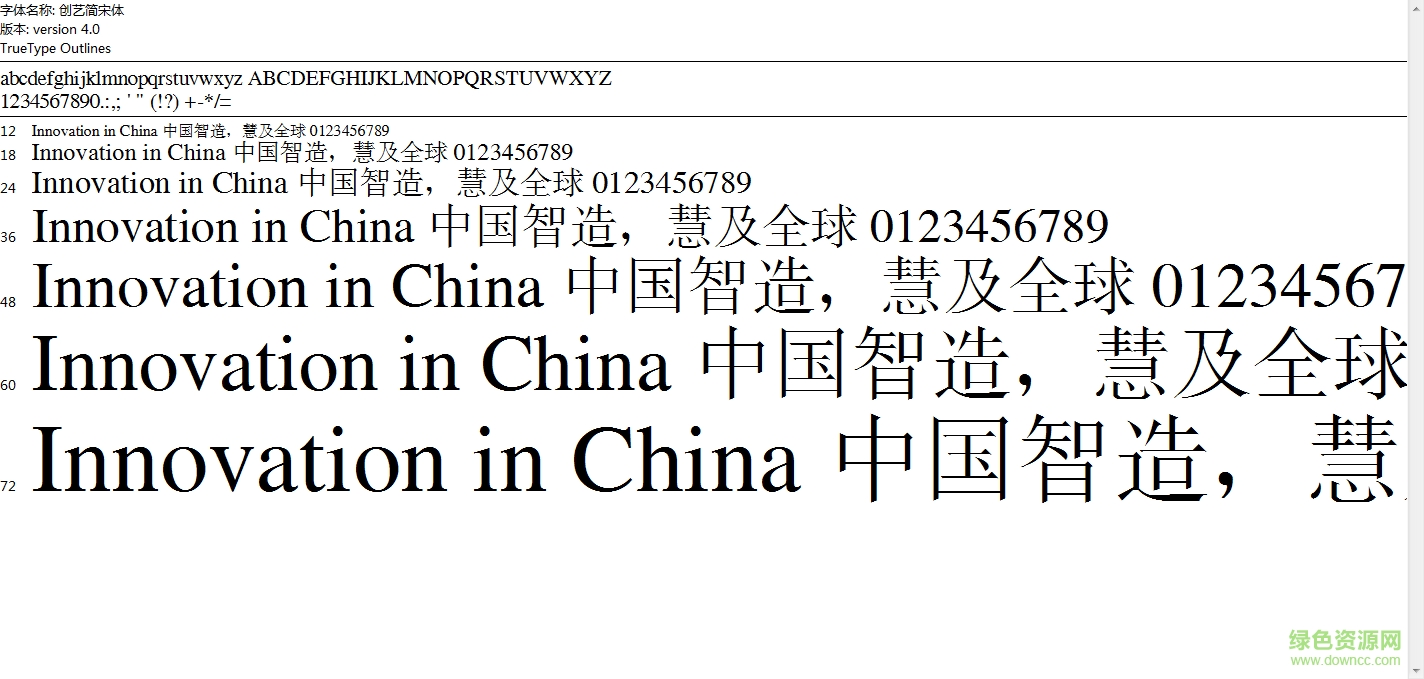
ctsongtisj字體又叫創(chuàng)藝簡宋體,是一款方方正正的宋體字體,線條流暢,字體清新,常常用于各種文章排版設(shè)計(jì)中,但是該字體也只應(yīng)用于一些特殊的文章中,所以很少見,如果你想做一些特殊的文字設(shè)計(jì),不妨使用一下該字體,感興趣的朋友就來綠色資源網(wǎng)下載吧!